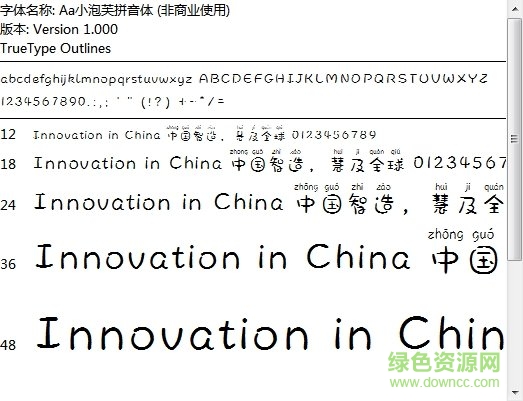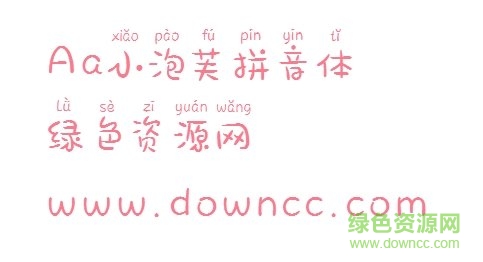
華為Aa小泡芙拼音體ttf
Aa小泡芙拼音體ttf是一款非??蓯鄣?a href="http://kiwanis-srv.org/k/pinyinziti/" target="_blank">拼音字體,不僅有著圓潤可愛的中文樣式,還有著清晰生動的拼音注釋,喜歡的朋友就來綠色資源網(wǎng)搶先體驗吧!
泡芙拼音字體ttf特色
泡芙拼音體,是aa字體管家推出的一款卡通字體,每個中文漢字上有著對應(yīng)的拼音標(biāo)注,讓你在面對各種生僻字時都可以快速讀出來,而字跡也充滿了童真童稚的趣味,可以適用于平面設(shè)計、海報創(chuàng)意等諸多領(lǐng)域。